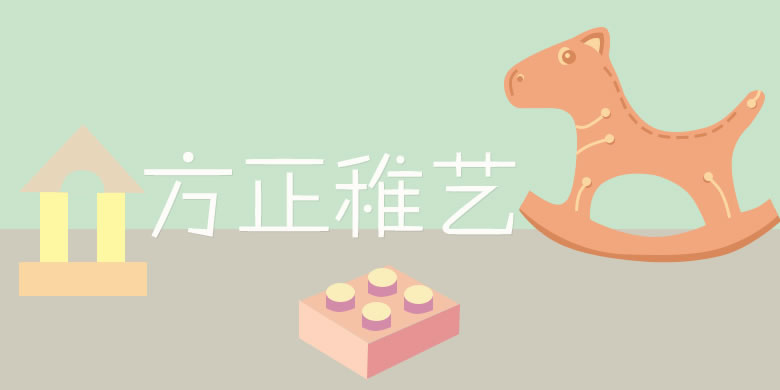
方正稚艺是一款富有孩童气息的创意字体。这款字体的笔形主要是由圆点和直线构成,重心偏低,有儿童书写的简拙;笔画交接处多有书写意味的分离,笔画中圆形的点画与其他直线笔画形成对比,灵动可爱。字形轮廓整体统一,具有一定的易读性。方正稚艺的个性乖巧灵活,清新萌动。不但适用于儿童类的书刊、品牌广告和产品包装设计,以及社交网络的个性化用字,还可胜任简短的正文排版。